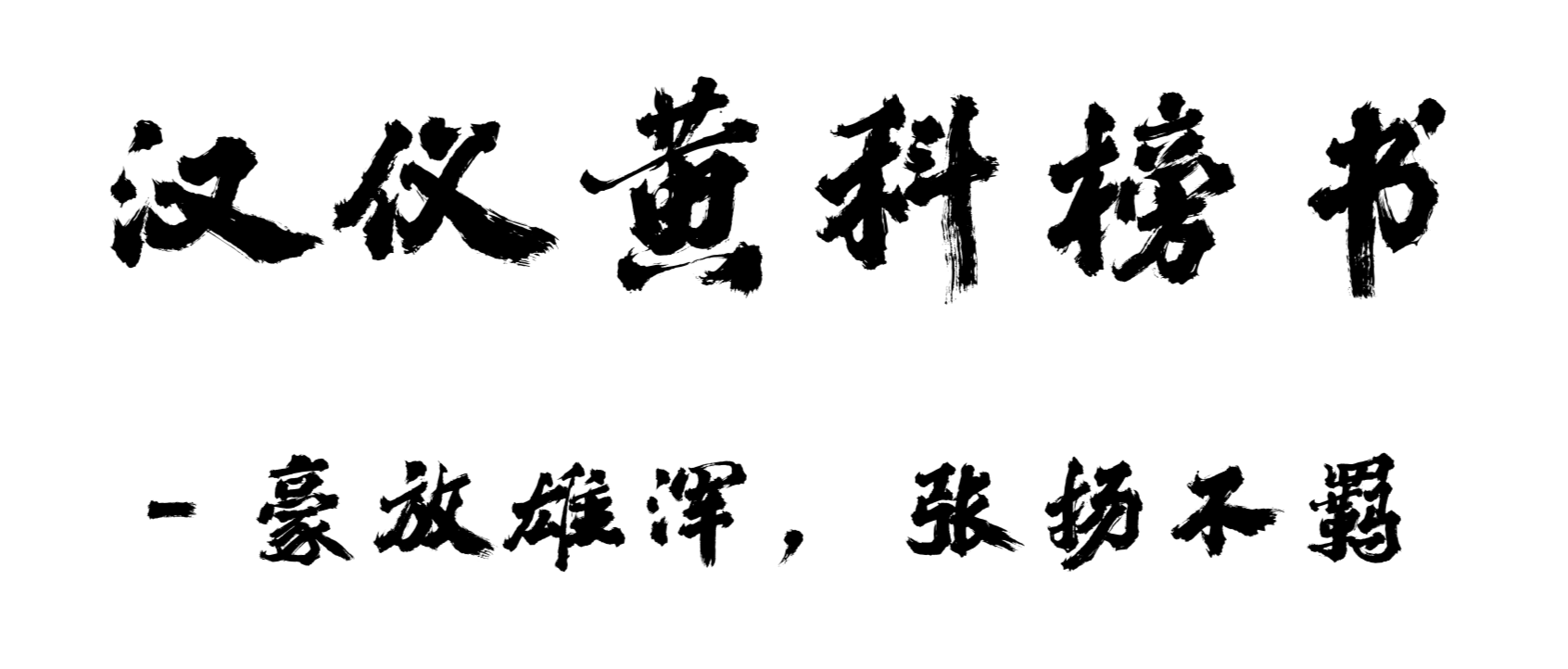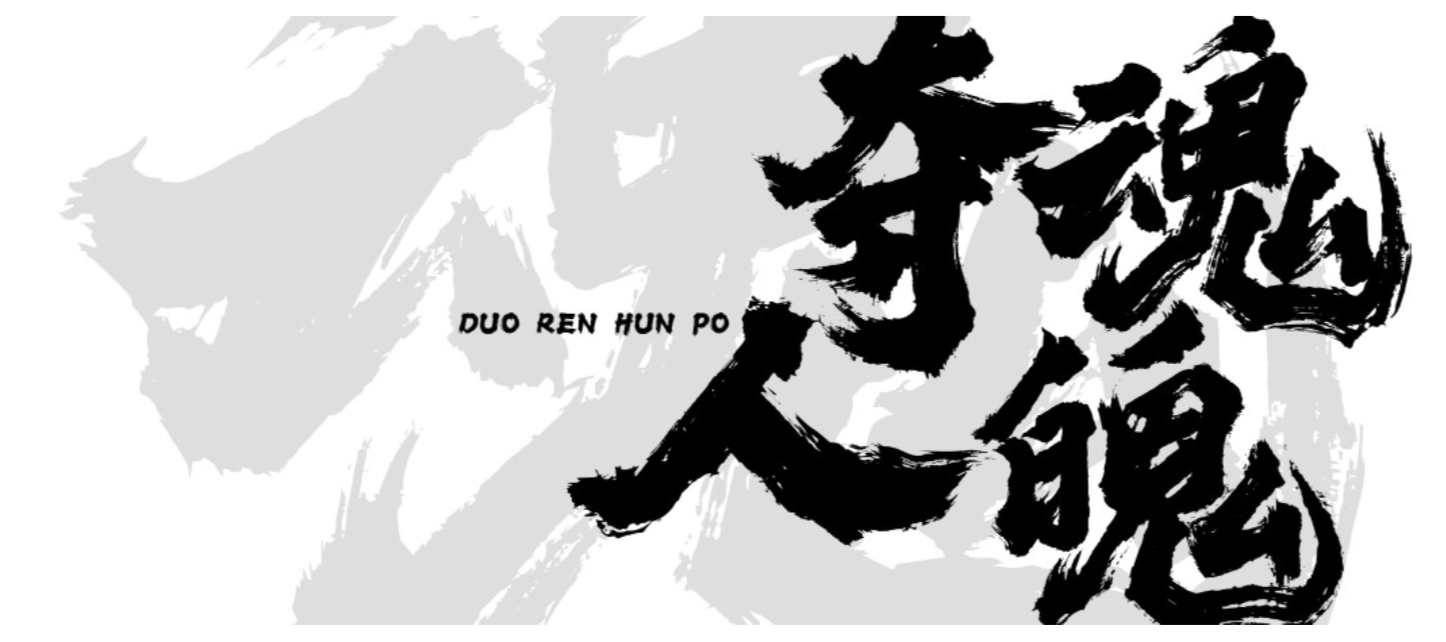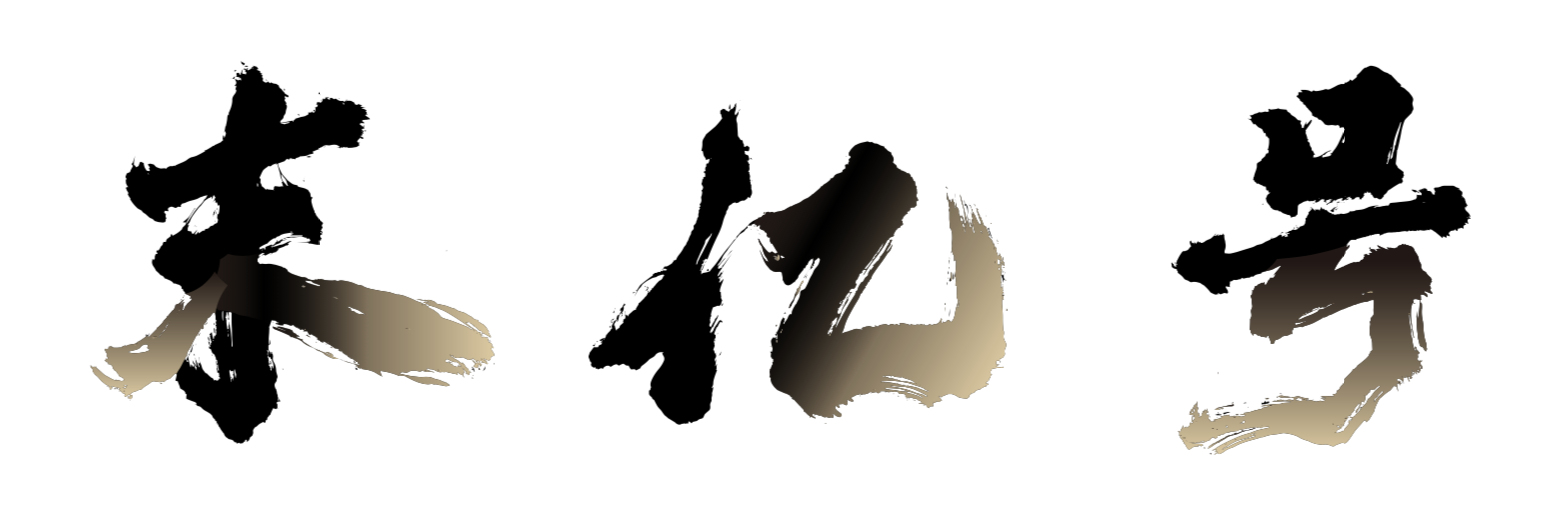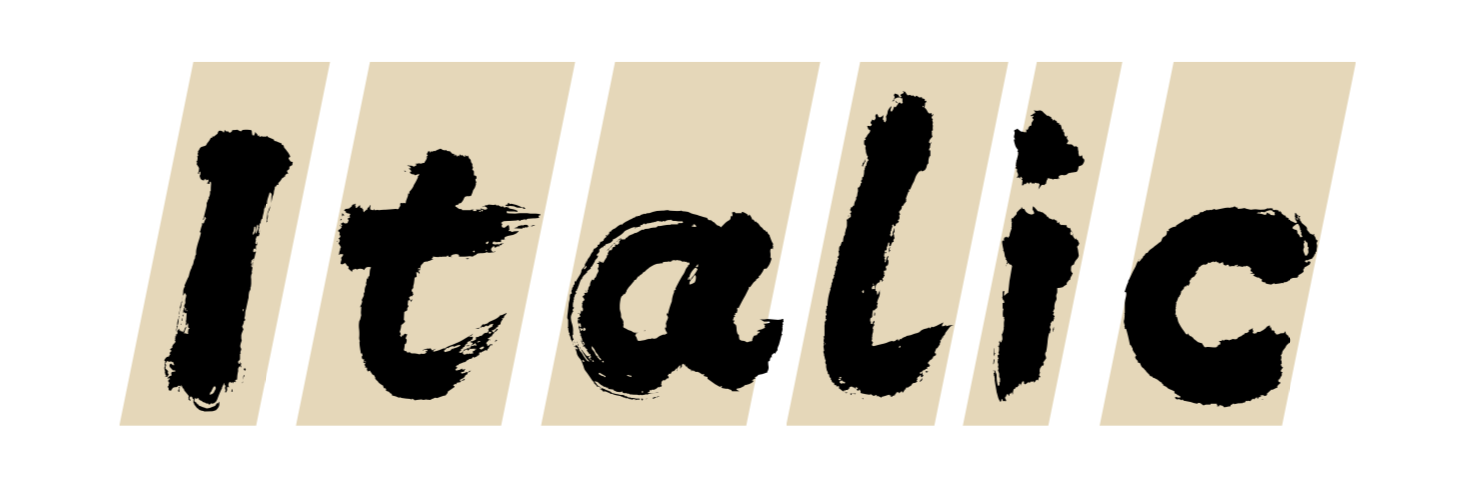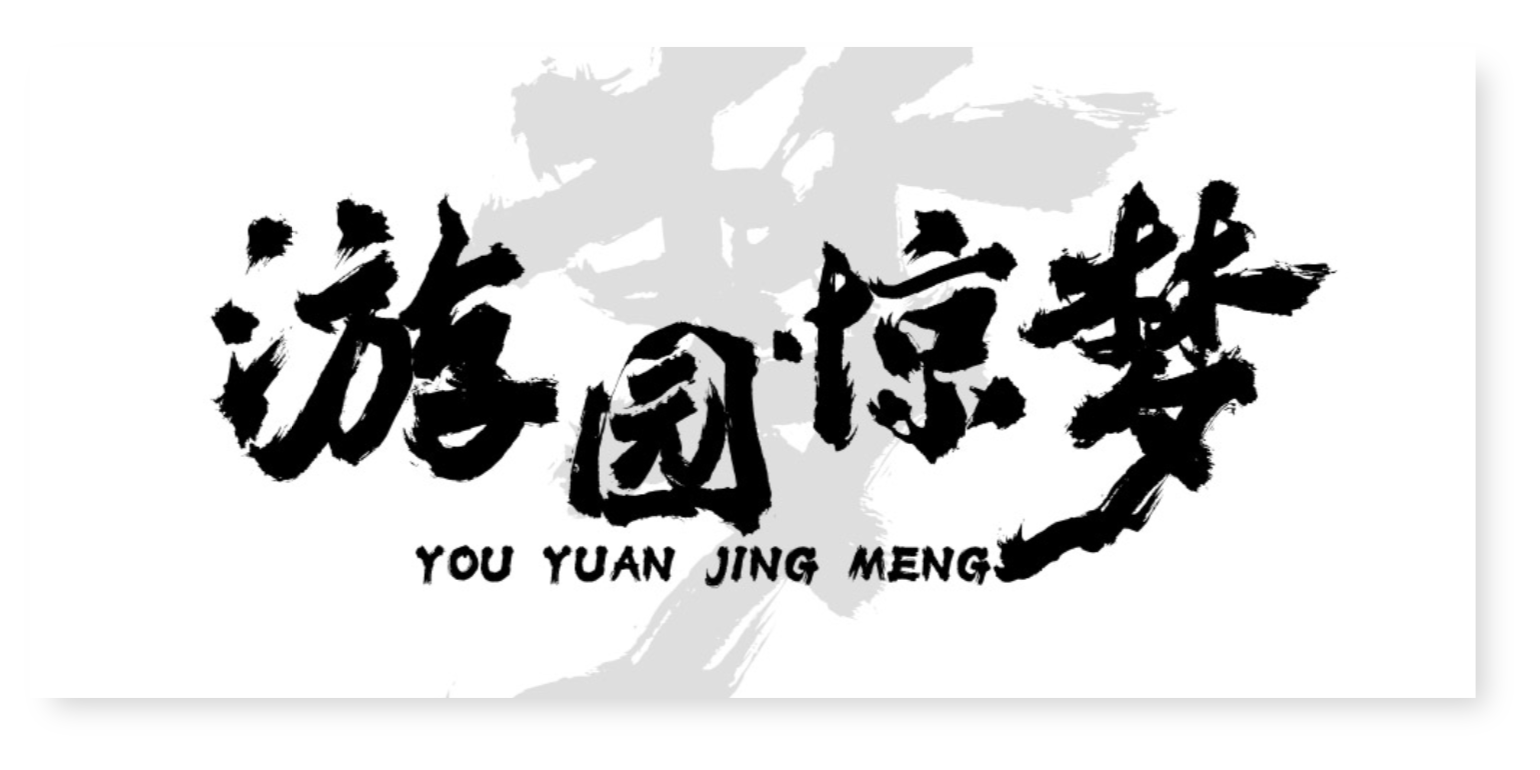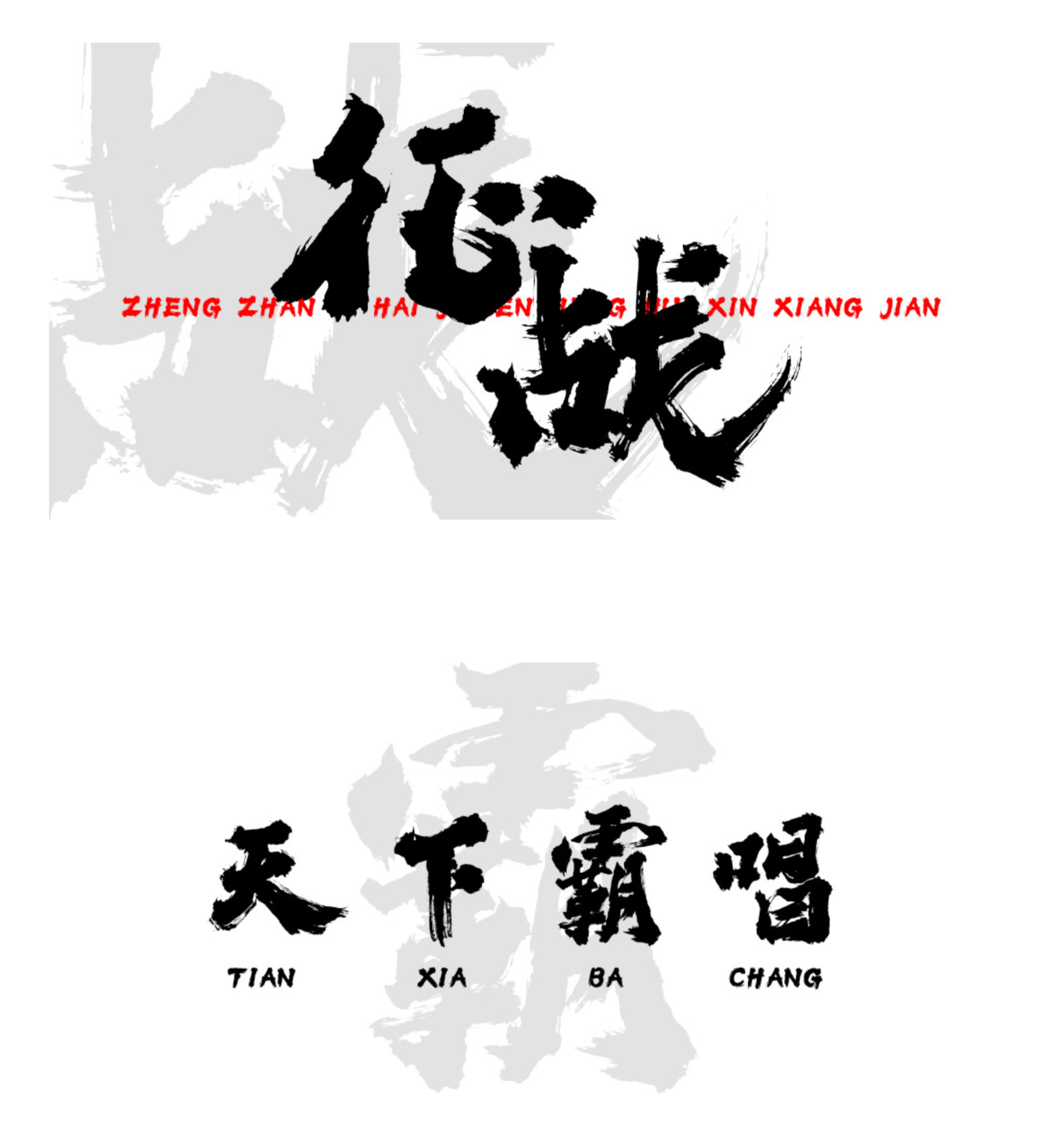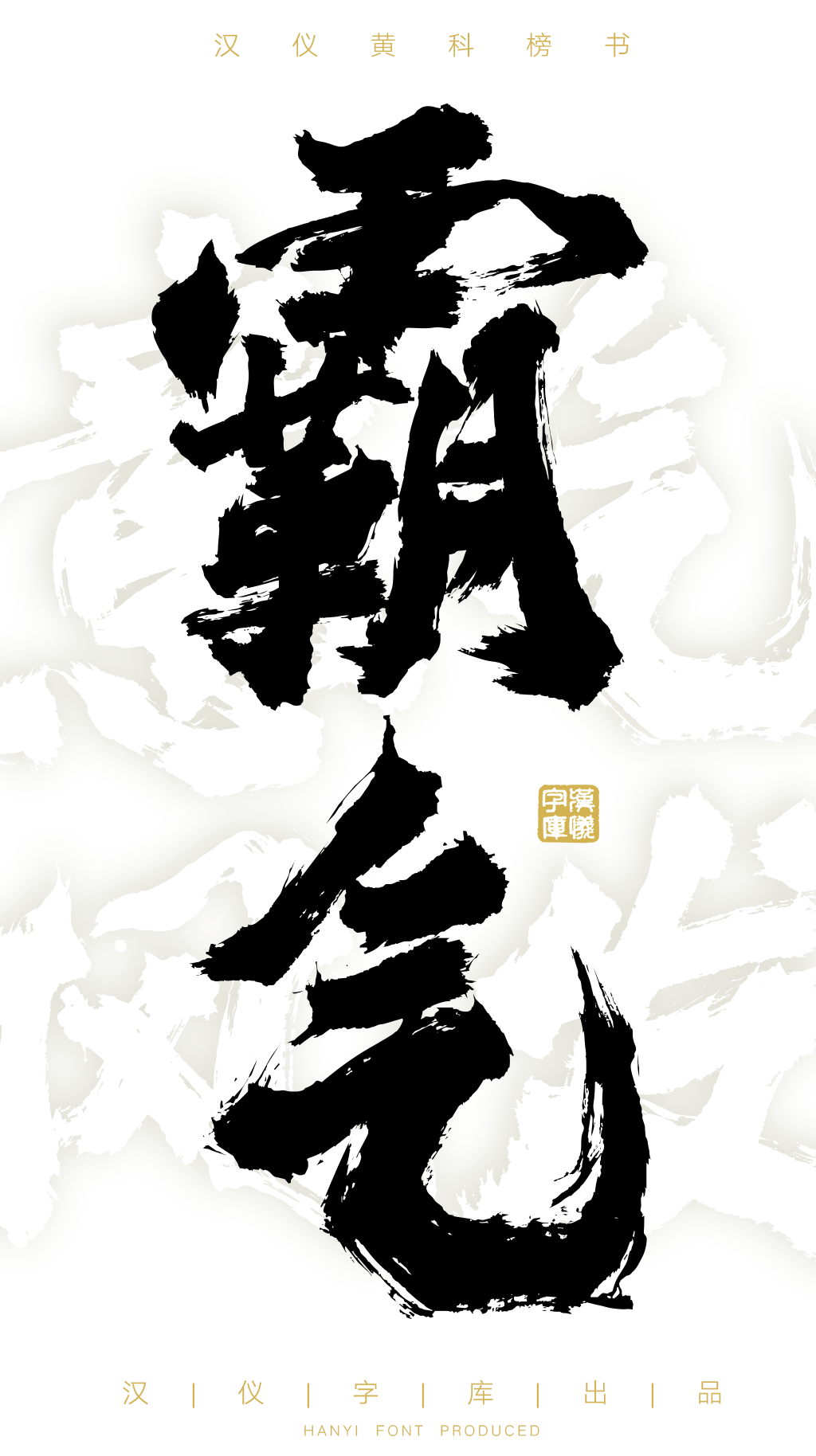
一款张扬不羁,“夺人魂魄”的字体
汉仪黄科榜书 | 键盘时代的书写者
汉仪黄科榜书由当代青年书法家、汉仪字库签约书写人黄科创作。
黄科笔名半步阿森,他师承著名书法家,剧作家,诗词楹联学家钱法成先生。黄科的书法风格多变,从传统中来又能区别于传统书法,更具现代感。他的字视觉冲击力强大,形式美感与设计感十足,冲破了条条框框的束缚,大胆的同各种现代与商业元素融合,呈现了一派全新的气象。正是这种在尊重传统书法艺术的基础上的勇敢突破使得黄科在商业书法领域里独树一帜。他的书法被大量的商业应用。诸如游戏LOGO,影视剧片名,服装纹样与大空间装饰等。
黄科的巨幅书法作品严格意义上说来,已经脱离了书法,而是与空间紧密结合的现代艺术。用纸墨的黑白效果及浓淡干枯的强烈对比,与疏密跌宕的排篇布局,在相应空间内形成巨大的视觉聚焦点的作用。区别于传统榜书大字的平正求稳,而是大胆的追求力量的释放与章法的险绝。
汉仪黄科榜书 | 风格豪放大气
榜书俗称大字,古称“署书”或“擘窠大字”,明代费灜《大书长语》曰:“秦废古文,书存八体,其曰署书者,以大字题署宫殿匾额也。汉高帝未央宫前殿成,命萧何题额……此署书之始也。”
榜书的主要特点就是大,而汉仪黄科榜书的“大”主要表现为3点:
1、字大。黄科在做这款字体时,一个字即是一张纸的大小。透过手稿我们能够感受到中国书法那种大气磅礴、浑厚雄健的精神,给人以强烈的视觉震撼力。
2、占容量大。我们在制作字库时,将字体丰富的笔触完整的保留下来,做到了最大程度的细节还原,这使得汉仪黄科榜书的字体包相较其他字体大一些。
3、风格大气豪放。汉仪黄科榜书的笔力雄浑,笔势豪放,表现出了一种大气美。
汉仪黄科榜书是作者在充分吸取传统书法艺术精髓的基础上融入视觉艺术的一种具有强烈个人风格的特色榜书。重墨酣畅淋漓下既有飘逸跌宕的气质,又有转折豪放的形态,排篇布局层次错落疏密有变,墨色干枯相映,极具强烈的视觉冲击力和设计感。
汉仪黄科榜书 | 结构饱满雄浑
汉仪黄科榜书字体结构整体黑大于白、饱满雄浑、气势雄壮,给人以凝重、遒劲、坚毅泼辣之美感。这增加了字体在组合排版使用时的冲击感和力量感。
汉仪黄科榜书硬朗粗狂、张扬不羁的书写风格使其在形式美感上区别于传统榜书。它有着鲜明的个人风格,极具现代感与大空间装饰性。
汉仪黄科榜书 | 行笔干净利落
汉仪黄科榜书在笔画上多采用折笔直线,行笔爽利干脆毫不拖泥带水。展现出了字体“硬辣雄健”的性格形象。
黄科的书法功底十分深厚,他用笔简洁凝练,运笔坚实有力,几乎每一个字都有飞白,力量感十足。
汉仪黄科榜书 | 中西文匹配
汉仪黄科榜书的西文字母采用有倾斜度的西文书法Italic script(意大利书法体)风格为基础来配合中文。
汉仪黄科榜书西文字母的设计,参考并借鉴了中文笔画的书写方式,笔触丰富,手写感强,中西文搭配使用和谐统一。
汉仪黄科榜书 | 排版效果
汉仪黄科榜书的笔画粗重,视觉冲击力强,适合作为大标题使用。建议用户在设计时将标题文字拆分为单字进行排版,注意字与字之间要紧凑、文字大小要有变化、标题文字错位摆放,以下为案例效果:
汉仪黄科榜书 | 海报展示